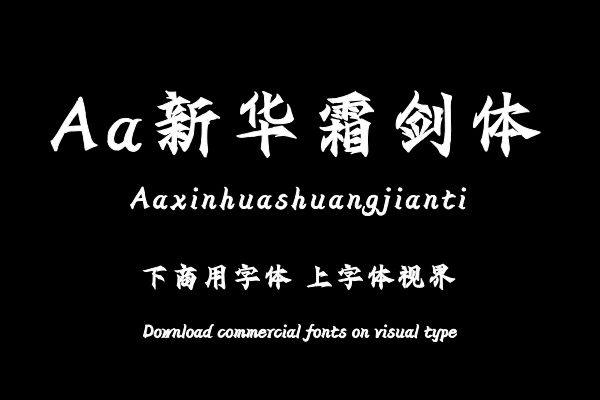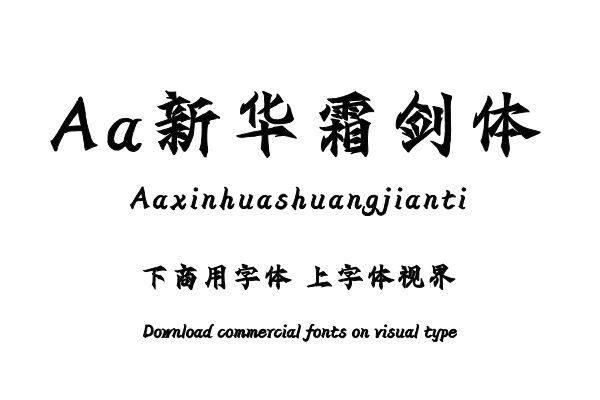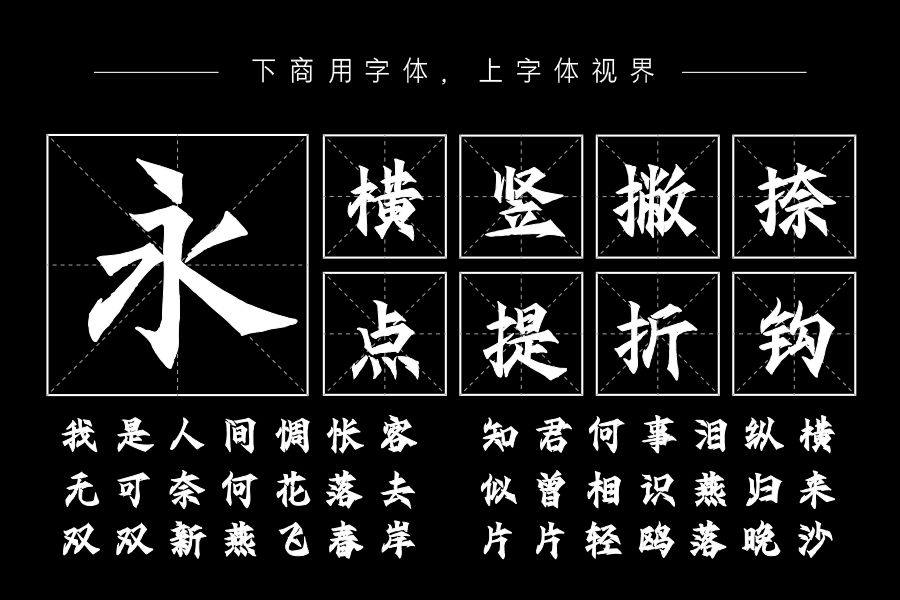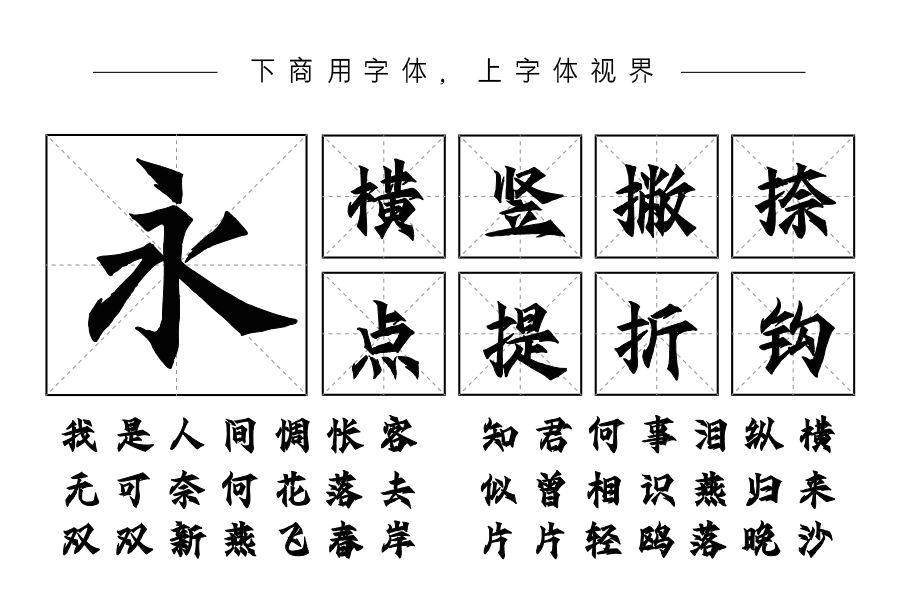
结合书法艺术与作者本人的美术字功底,在手写的随意性和美术字的规范性之间取得新的平衡。坚定的笔形,石刻一般的尖角构成这款源自魏碑特点的楷书,其偏向几何性的轮廓又与......购买须知:“下载服务费”与“字体VIP”所获得字体 仅用于个人非商用, 商用请联系付费授权。本字体为电脑用字,手机没有root权限不支持直接手机换字(手机如何root,请自行百度搜索教程)。购买前请先 了解清楚后再付款 ,字体为虚拟产品无法回收 一旦购买不支持退款。